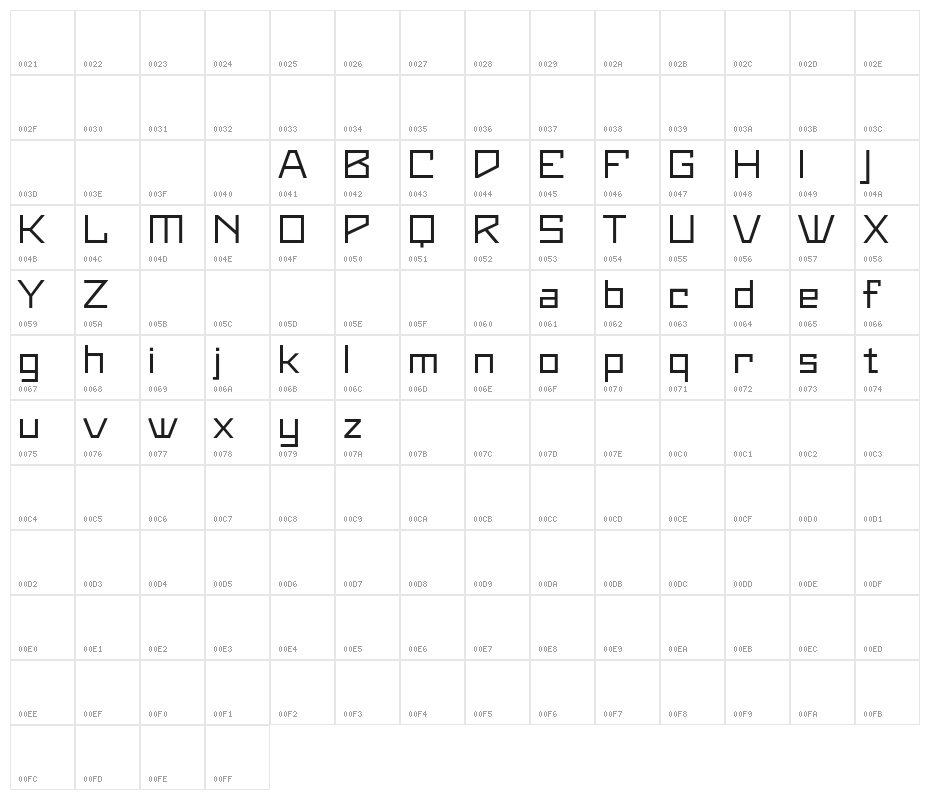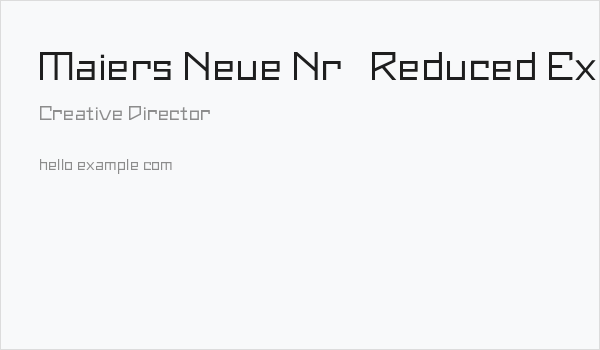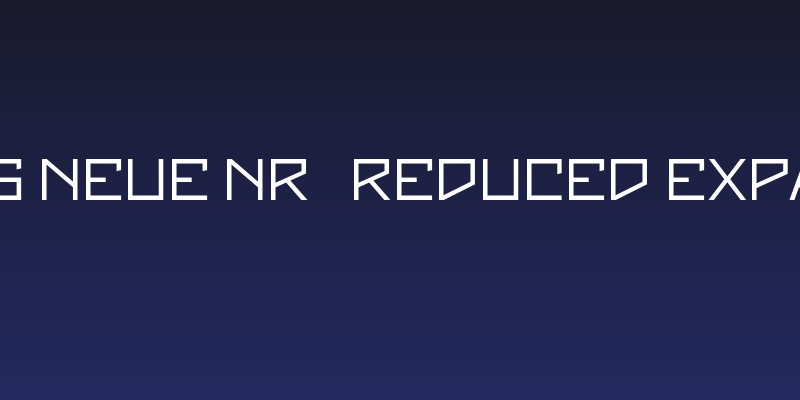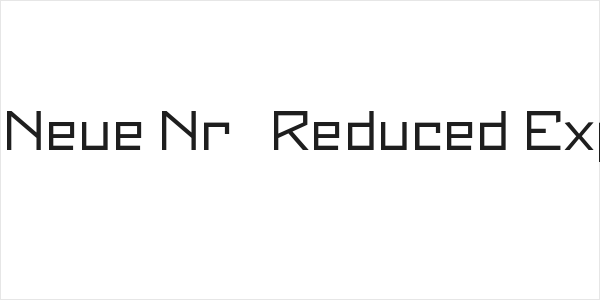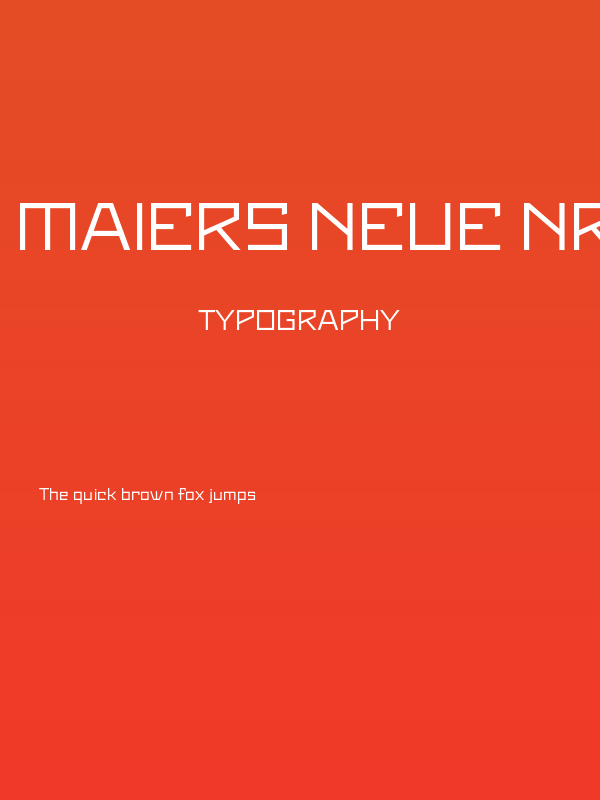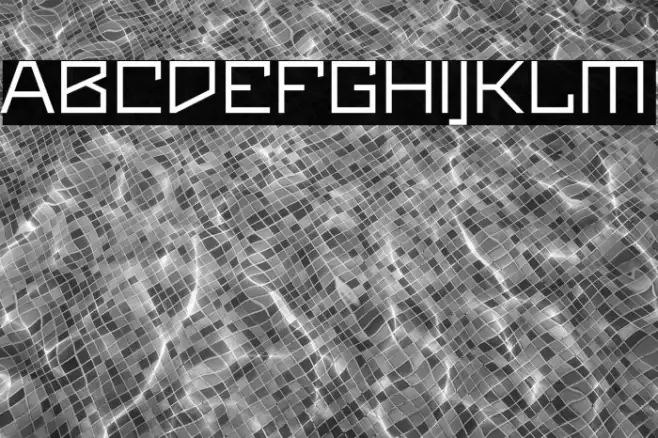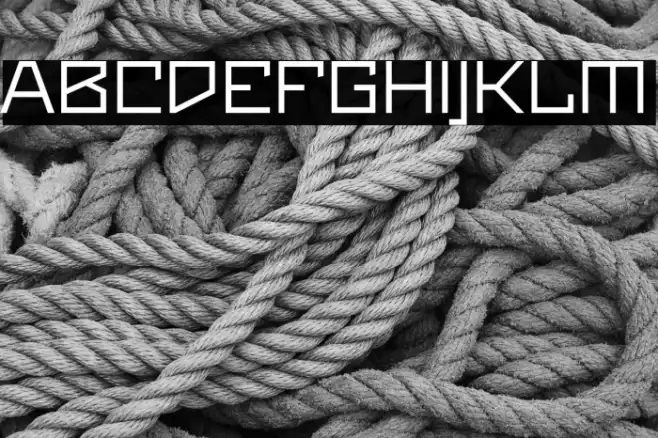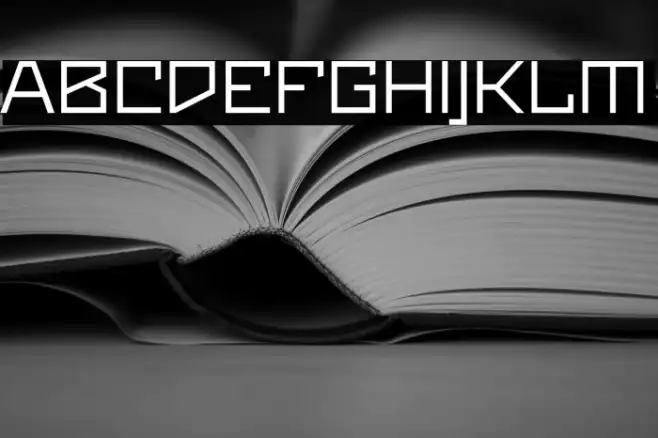
Maiers Neue Nr.8 Reduced Expanded Font
| Name | Maiers Neue Nr.8 Reduced Expanded |
| Schriften Familie | MaiersNeueNr.Reduced-Expanded |
| Style | Expanded |
| Kategorien | Futuristic |
| Gesamtstil | Modern, Technical |
| Anwendungsfall | Logos, Headlines, Digital Interfaces |
| Vorgeschlagene Projekte | Ideal for technology branding, modern posters, digital interfaces, and architectural designs. |